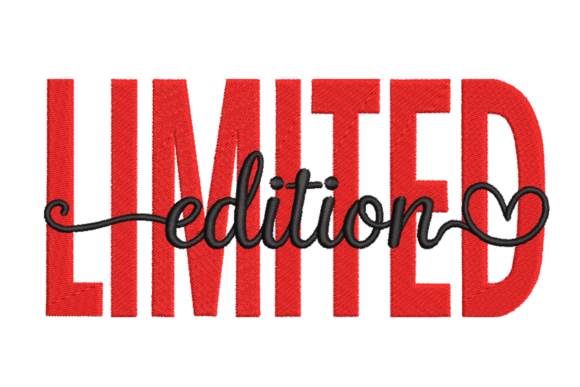
Limited Edition Quote
Jika anda sedang mencari aset berkualiti tinggi seperti Limited Edition Quote, pakej premium ini merupakan pilihan yang hebat untuk projek kreatif anda.
Dicipta dengan ketepatan, Limited Edition Quote menyediakan vektor yang bersih, tipografi yang licin dan lesen komersial untuk ketenangan fikiran.